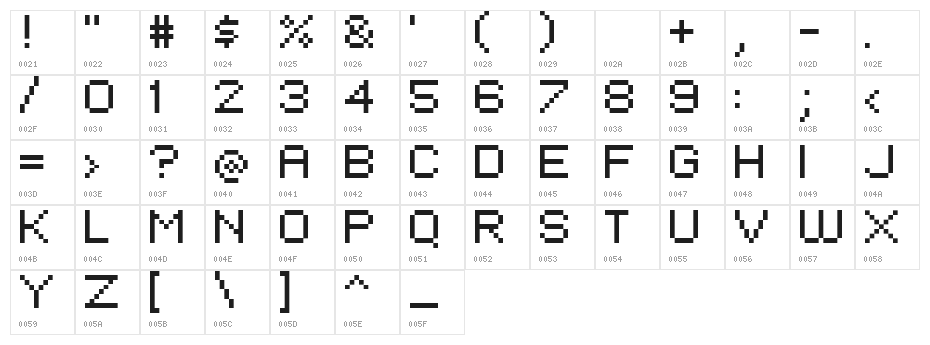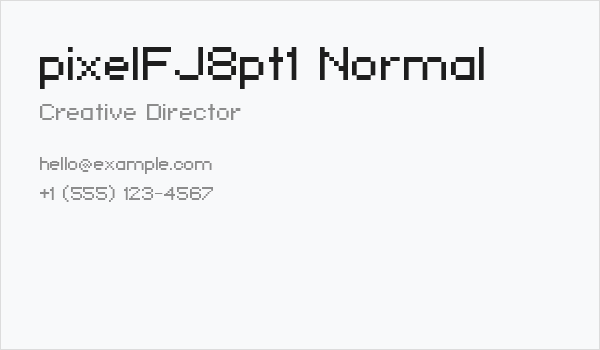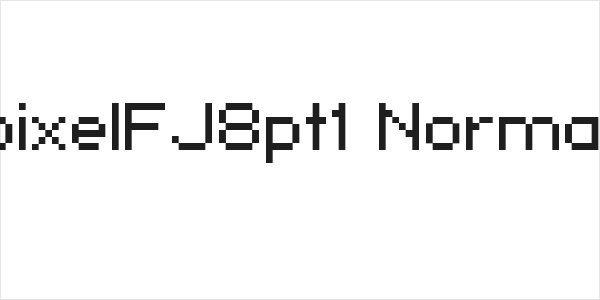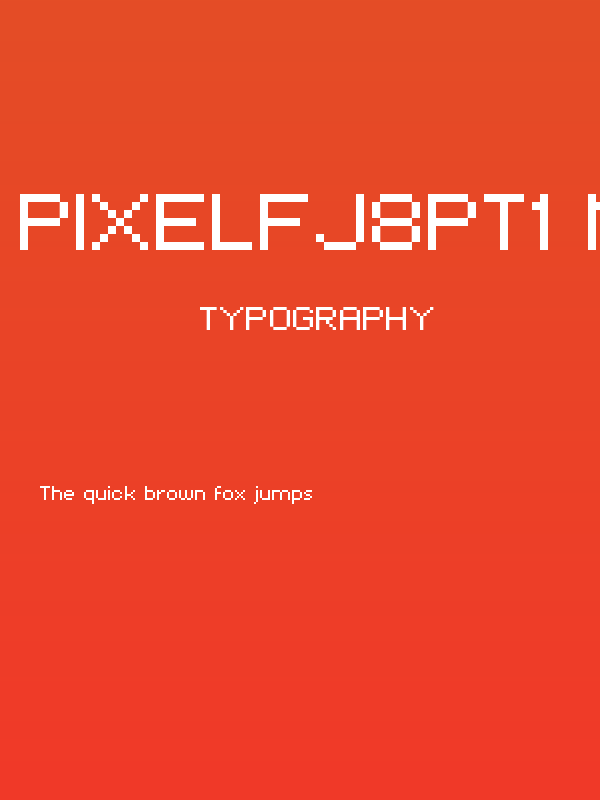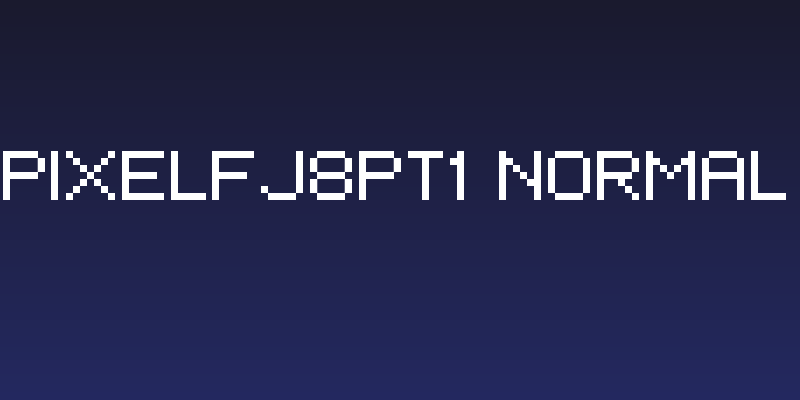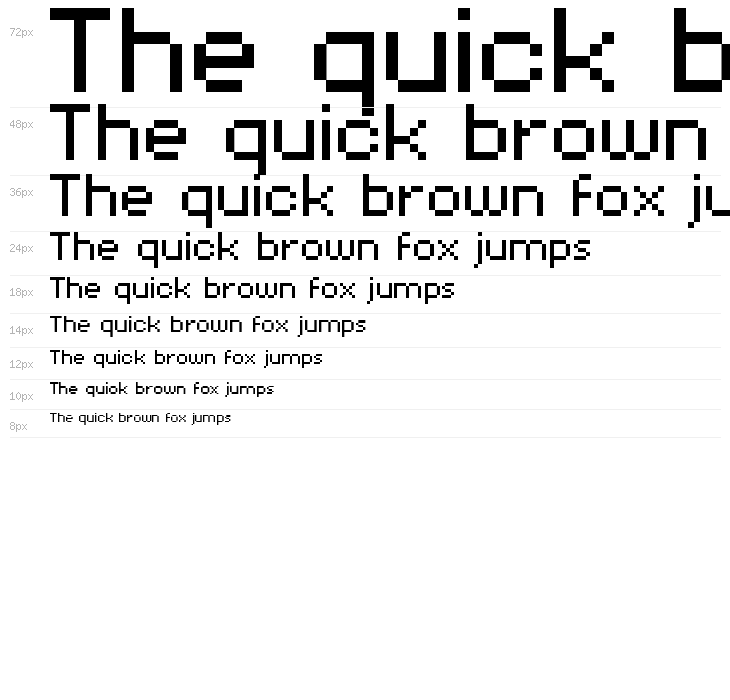
pixelFJ8pt1 Normal Font
| Категория | Pixel |
| Общий стиль | Retro |
| Область применения | Digital displays, video game text, retro-themed designs. |
| Рекомендуемые проекты | Ideal for retro video games, digital art projects, and any design work that requires a nostalgic or minimalist digital look. |